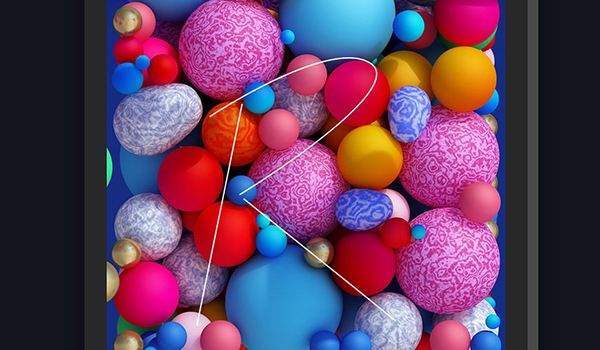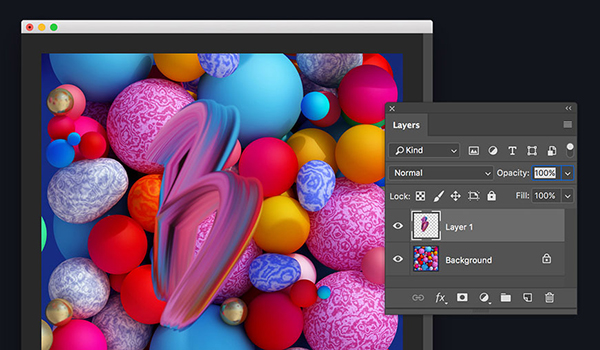
如何用Photoshop软件涂抹一个色彩斑斓的油漆字体
让我们一起去撸个五彩斑斓的油漆字体!
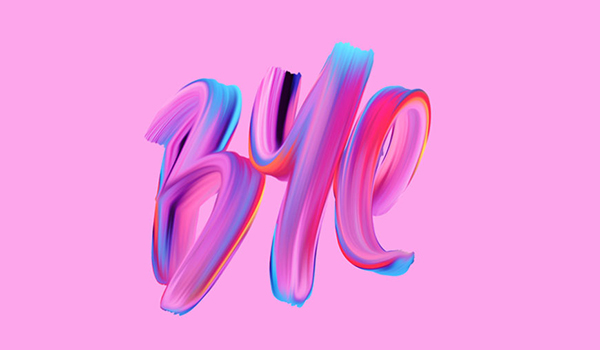
步骤1:首先在Adobe Photoshop CC中打开两个文档:一个彩色图像,一个是新的空白文档,或者直接新建一个图层。
步骤2:在彩色图层中,选择涂抹工具并选择具有大量纹理的涂抹刷,将其强度设置为95%,并勾选对所有图层取样,记得一定要勾选哦。
步骤3:在新图层上,选择纹理较多的笔刷,大小设置为100像素,在画面上直接涂抹出你要的文字,如果想要把文字涂的很精细,可以选择先勾画出字体的形状再涂抹。
步骤4:选择移动工具,然后将该字母拖到空白文档中,就可以看清涂抹后的整体效果了,是不是很神奇很迅速。
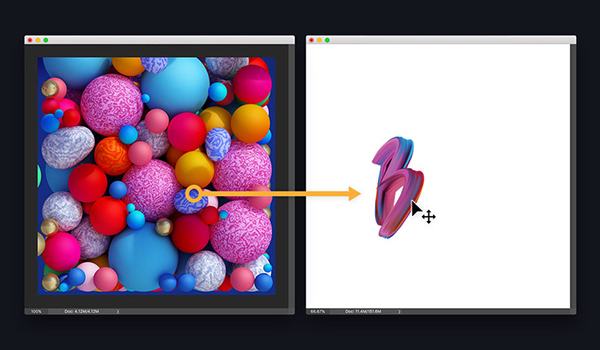
步骤5:回到彩色图层中,关闭刚刚创建的字母的可见性,然后重复步骤3和4,涂抹其他两个字母,组合在一起如图,就这么快就撸好了。~~
那么如何精致的画出字母再涂抹呢?详细步骤如下:
步骤1:在彩色图像图层中,创建一个新的图层,然后选择钢笔工具并将其设置为路径。
步骤2:用钢笔工具绘制字母的各个笔划,绘制一个笔划后,按Esc结束它并开始一个新笔划。
步骤3:打开“路径”面板,将会看到刚刚使用钢笔工具制作的字母,选择“涂抹”工具,根据自己的喜好调整设置,然后在“路径”面板中,单击“描边路径”,Photoshop会自动沿着绘制的路径涂抹。就这么简单,去试试挖~~